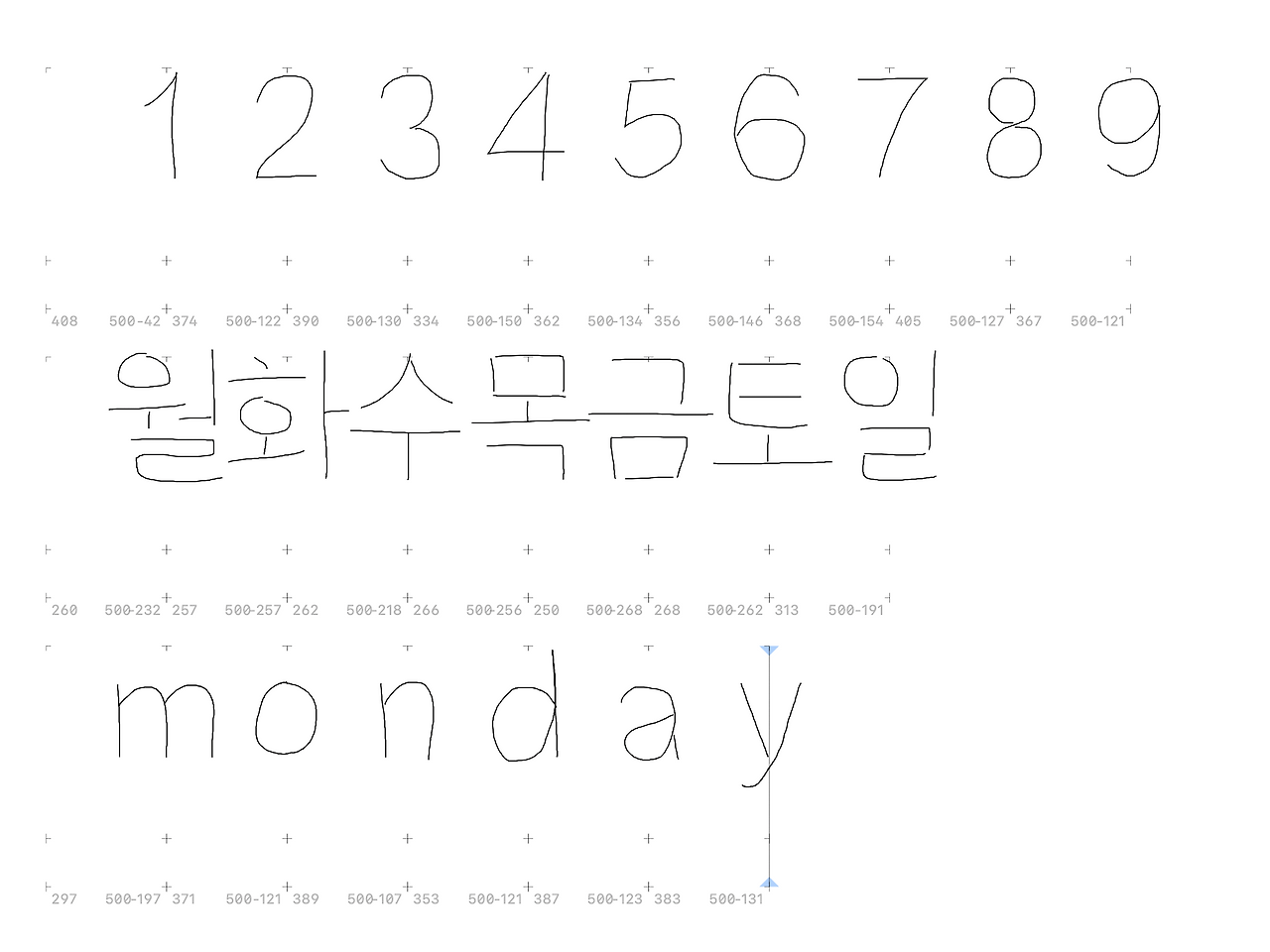
2026년 손글씨 캘린더 폰트
오로지 한글, 한자, 숫자 달력 글자만 가능한 폰트에디터를 만들었습니다. 사실 저 글자들은 애니메이션이 됩니다. (기록한 그대로)
가족의 손글씨로 만들어진 달력, 아이들 글씨로 만들어진 달력용으로 2026년을 준비합니다. 물론 폰트라서 앱에서 가족이 쓴 17자의 글씨로 달력, 시간을 보여주며 손글씨는 전체 제작도 어플에서 가능합니다.
베리어블폰트라서 두께가 자유롭게 변경되어 글꼴 하나로 10여 가지 글꼴처럼 보입니다.
+ 영문, 한자, Moon 15 약물을 쓰면 전세계 대부분 사람들이 볼 수 있는 달력폰트가 됩니다. (실제구현 캘린더, 가계부 전문 출판사)
오직 저희 책 구매자에게만 제공할 목적으로 개발 2년 넘게 개발해서 겨우 17자만 쓰는 프로젝트가 된 이유를 먼저 정리해 보자면 인공지능도 사람 손글씨는 쉽게 폰트로 못 만듭니다. 사람이 투여돼야 하고 AI로 만든다는 서비스들이 몇 년 전에만 잠깐 반짝하고 잘 안 되는 이유가 하나 있습니다. 10만 원이라고 해도 디자이너가 폰트를 마지막에 손봐야 해요. 30일 걸리는데는 사람이 주문온 것을 다 처리해야 하는데 펀딩에 성공하는 순간 디자이너를 뽑아서 써야하는데 인건비가 안맞아요.
그래서 펀딩 성공후 홍보효과로 저렴한 손글씨 폰트는 거의 사라졌어요.
그리고 비슷비슷한 두꺼운 폰트로 만들어지는 것도 두꺼우면 잘 모르거든요 ^^ 저는 그걸 못 참아서 3D로 폰트를 균일화하게 하기 위해 획을 돌려보고 여러 가지 실험을 2년 넘게 해 봤습니다. 비슷한 폰트 ≠ 손글씨가 아니라는 판단으로 전 세계 글자를 다 쓰는 걸 여전히 혼자만의 프로젝트로 하고 있습니다.
가는 볼펜의 어머님 손글씨 폰트로 11172자를 그려야 하는데 그건 무리고 3000자는 써야합니다. 1벌로는 사람의 손글씨가 되기 힘들어요. 사람은 그때그때 다르게 쓰기 때문입니다. 그걸 다 고려해서 R 이라는 개념의 폰트를 구상했는데 너무 무거운 파일이 되어 실사용 목적으로 어울리지 않아 포기했습니다. 사람의 글씨를 폰트 하나로 정형화 하기 힘들기 때문에 여러실험을 해온 기록은 브런치 안에 있습니다.